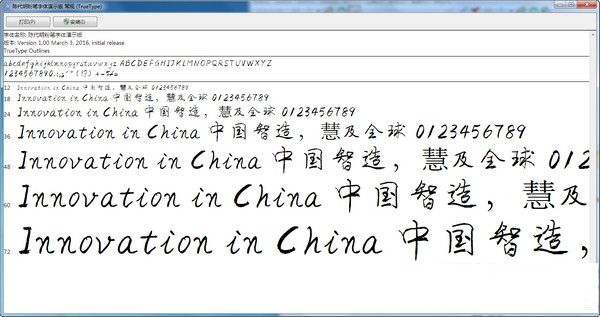
手寫粉筆字體是一款漂亮的英文字體,支持中英文顯示,非常適合用在廣告設(shè)計(jì)或海報(bào)設(shè)計(jì)領(lǐng)域,有興趣的朋友快來綠色資源網(wǎng)下載吧!
字體造型生動(dòng)活潑,有鮮明的節(jié)奏韻律感,色彩豐富明快,給人以生機(jī)盎然的感受。具有美觀大方,便于閱讀和識(shí)別,應(yīng)用范圍廣等優(yōu)點(diǎn)!